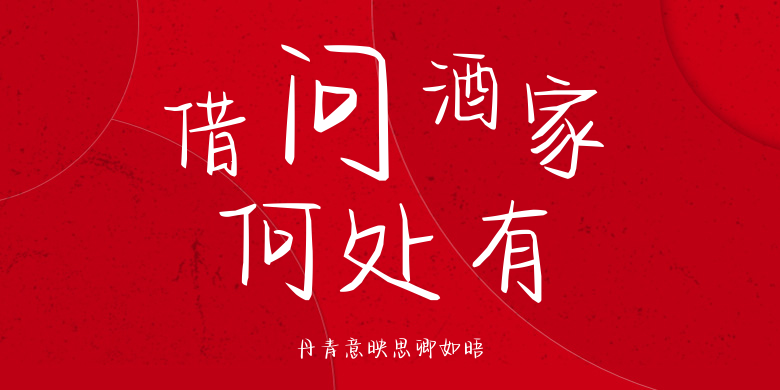
丹青意映思卿如晤
丹青意映思卿如晤,这款字体结构工整、笔画清晰,兼顾美观与易读性,适用于标题、正文、海报、包装、LOGO 等多种场景。字形优雅稳定,风格百搭耐看,适配日常排版与创意设计,让文字呈现更舒适、更具质感。丹青意映思卿如晤一笔一画,皆是细节,以均衡的比例、流畅的线条打造舒适视觉体验,字形端正大气,风格简约现代。无论是商业设计、品牌宣传还是日常排版,都能轻松驾驭,让文字更有格调与力量。丹青意映思卿如晤字体下载。